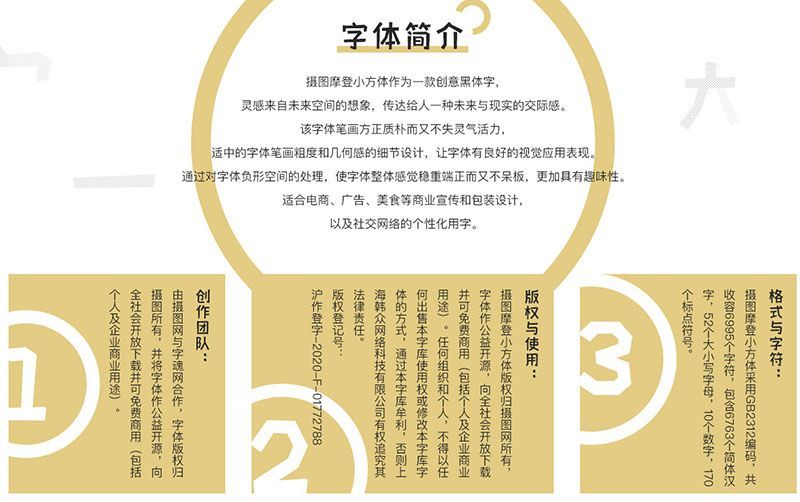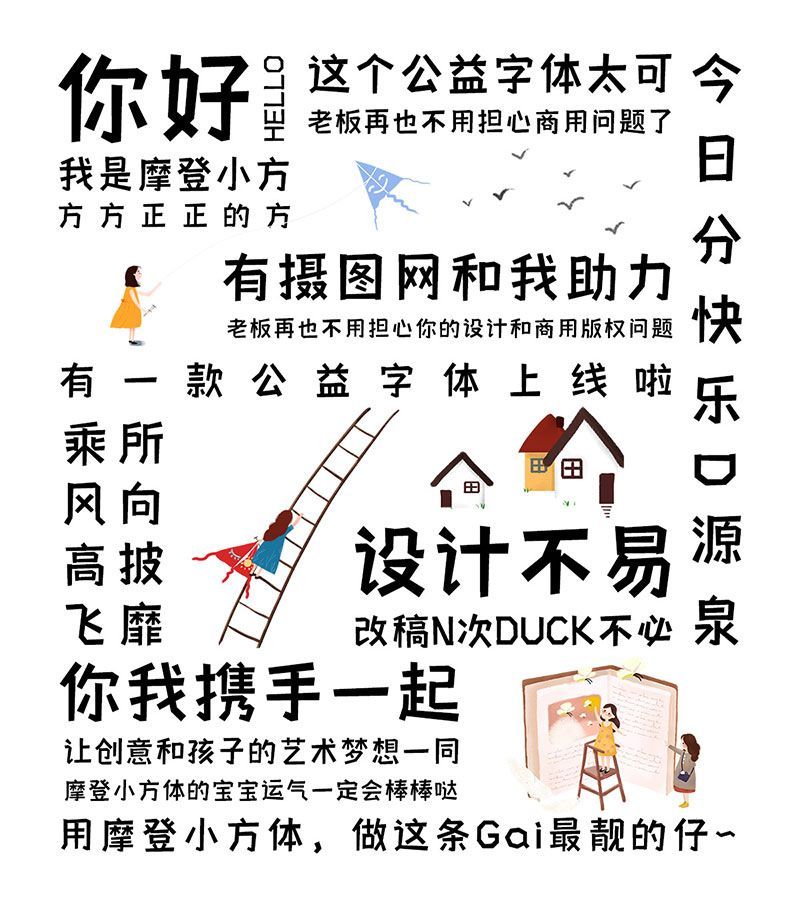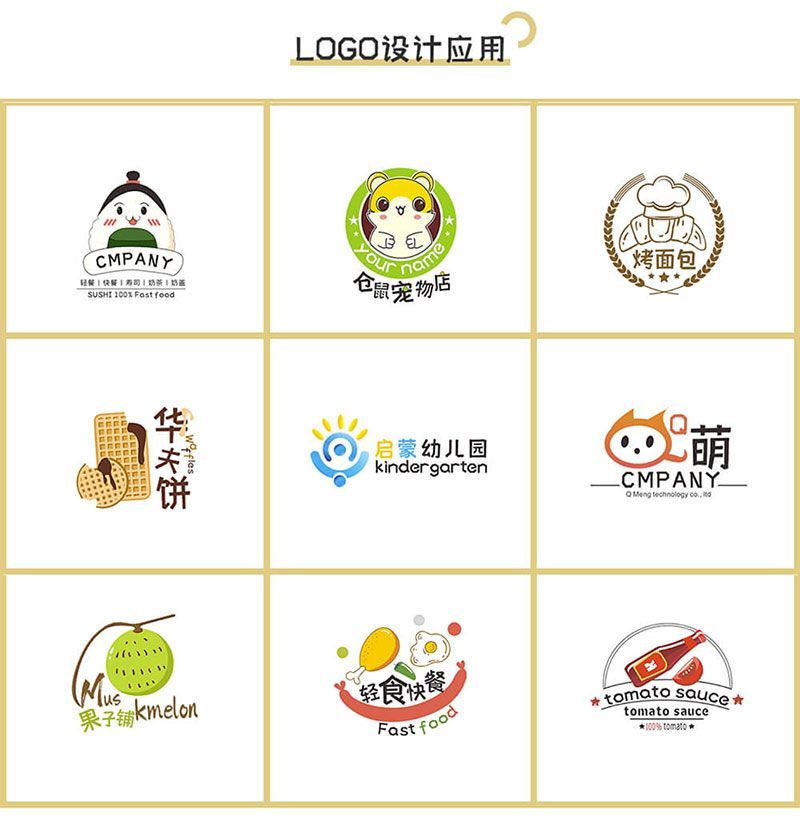
摄图摩登小方体是摄图网联合国内专业字体设计机构iFonts共同推出的一款公益创意黑体字,摄图摩登小方体作为一款创意黑体字,灵感来自未来空间的想象,传达给人一种未来与现实的交际感。该字体笔画整质而又不失灵气活力,适中的字体笔画粗度和几何感的细节设计,让字体有良好的视觉应用表现。通过对字体负形空间的处理,使字体整体感觉稳重端正而又不呆板,更加具有趣味性。适合电商、广告、美食等商业宣传和包装设计,以及社交网络的个性化用字。